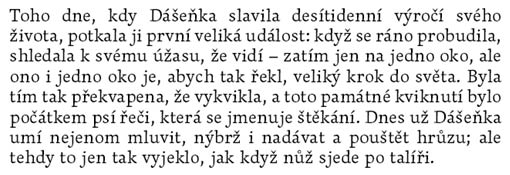
Typografie odborného textu - doplňující texty
2 Klasifikace písma Československá klasifikace písem (kterou zde uvedeme jako jedinou z mnoha možných klasifikací) je dílem typografa Jana Solpery. Tato klasifikace nerespektuje přesně chronologický vývoj, ale především dělí písma podle vzhledu a charakteristických znaků do jedenácti skupin (uvádíme deset), přičemž každá obsahuje další podskupiny: Dynamická antikva Přechodová antikva Statická antikva Lineární písmo serifové Lineární bezserifové statické písmo Lineární bezserifové dynamické písmo Lineární antikva Kaligrafická písma Volně psaná písma Písma lomená Dynamická antikva Do této skupiny řadíme renesanční antikvy vytvořené od druhé poloviny 15. století do první poloviny 18. století (a jejich moderní modifikace). Používá se především jako knižní písmo, pozdější varianty jsou univerzálně použitelné. Dynamická antikva pozdně renesanční Adobe Caslon Pro Přechodová antikva Jako přechodové antikvy označujeme písma z druhé poloviny 18. století a jejich moderní modifikace. Písma vytváří přechod mezi dynamickými písmy (inspirovanými ručně psanými znaky) a písmy konstruovanými (statická antikva). Tato písma se využívají jako knižní s širokou použitelností. Přechodová antikva Týfa Text Statická antikva Zahrnuje antikvy konce 18. a začátku 19. století a jejich moderní modifikace. Používá se jako knižní písmo zejména pro krásnou literaturu. Statická antikva didotovská Bodoni
3 Lineární písmo serifové Písma této kategorie vychází z egyptienek 19. století a jejich moderních modifikací. Tato písma slučují znaky antikvových a lineárních písem. Lineární písmo serifové, tzv. clarendon Clarendon Lineární bezserifové statické písmo Sem patří písma vycházející z grotesků 19. století a jejich moderních modifikací. Lineární bezserifové statické písmo grotesk Dyna Grotesk Lineární bezserifové dynamické písmo Navazuje na dynamické renesanční antikvy, používá se jako titulkové, ale i knižní písmo. Lineární bezserifové dynamické písmo s nakloněnou osou Gill Sans Lineární antikva Spojuje kresebné prvky antikvových a bezserifových písem, používá se jako knižní, časopisové nebo titulkové písmo. Lineární antikva s jemnými serify Copperplate Kaligrafická písma Vycházejí z kultivovaných kaligrafických skriptů, používá se jako titulkové písmo. Kaligrafické písmo dynamické Zapf Chancery
4 Volně psaná písma Vycházejí ze současných rukopisných skriptů, používají se jako titulková písma. Volně psaná lineární antikva Time Script Lomená písma Vyvíjela se od gotiky až do 19. století, používají se jako písma titulková a akcidenční. Lomené písmo fraktura Fette Fraktur
5 Klasifikace písma Písmová rodina Volbě písma bychom měli být velice obezřetní. Rozhodně bychom se neměli spokojit s písmem, jenž náš editor nabízí jako výchozí a starat se pouze o jeho velikost. Použitý font zančně ovlivní celou naši práci. Nikomu nedoporučujeme spolehnout se na font Times New Roman od Microsoftu, který v české modifikaci trpí značně nepovedenou diakritikou, navíc výsledek vypadá obvykle tuctově a kancelářsky. Přitom v samotném systému Windows nalezneme písma, která se pro sazbu hodí mnohem více. Jmenujme například font Georgia a v novějších instalacích aplikací od Microsoftu pak máme k dispozici například font Cambria. Pokud nám na výsledku záleží a chceme produkovat originálně zpracované texty, doporučujeme poohlédnout se po nějakém z nesystémových fontů. Je pravda, že většina kvalitních fontů je komerčních, ale existují písma, která můžeme používat zdarma, obsahují českou diakritiku a dobře vypadají. Uveďme zde alespoň písma Lido od Střešovické písmolijny a Gentium. Pro více fontů viz: Velikost písma Hovořit zde o velikosti písma může být značně zavádějící, neboť u každého fontu nabývá písmeno při stejné velikosti různé výšky. Pokud bychom snad přeci jen měli nějakou hodnotu doporučit, volili bychom stupeň 11. Musíme však toto variovat vzhledem ke zvolenému fontu, velikosti stránky a jejím okrajům. Doporučujeme stránku nejprve vysázet v různých stupních (například 10, 11 a 12), vytisknout, porovnat a podle výstupu finální velikost písma rozhodnout. Pokud kombinujeme více velikostí písma (pro odlišení jednotlivých úrovní nadpisů, či za jiným účelem), mělo by platit, že jednotlivé velikosti od sebe musí být jednoznačně odlišitelné volíme velikost tak, aby mezi jednotlivými použitými nebyl rozdíl velikosti méně než dva stupně. Kombinování písem Existuje pravidlo, které se hodí na většinu situací a jeho aplikací obvykle nic nezkazíme: Zvolme si jedno bezpatkové písmo jako nadpisové a jedno patkové (serifové) písmo na veškerý ostatní text. Nemusíme se tohoto pravidla striktně držet, ale mělo by platit, že rozdíly mezi jednotlivými použitými písmy by měly být výrazné, abychom čtenáři umožnili se v tatko členěném textu snadno orientovat. Použití několika velmi podobných písem by vedle sebe nevypadalo dobře a neplnilo by navigační úlohu.
6 Odstavec Hlavním a nejviditelnějším paramerem odstavce je jeho zarovnání. Pro sazbu odstavce máme čtyři možnosti: zarovnání na levý a na pravý praporek (na levou a pravou zarážku), na osu (nebo také na střed) zarovnání do bloku. Na levý praporek Tento způsob zarovnání se používá například pro sazbu veršů, často se používá pro úpravu odborných časopisů. V součastnosti jsme zvyklí vídat většinu souvislých textů zarovnaných do bloku, na sazbě na praporek však není nic špatného ani amatérského, takto zarovaný text je dobře čitelný a nehrozí nám komplikace jako u sazby do bloku (viz dále). Začátky jednotlivých řádků jsou zarovnány k levému okraji, konce řádků jsou ponechány volně, řádky jsou tedy různě dlouhé. Mezislovní mezery jsou stejné. Na pravý praporek Levý okraj řádků zůstává volný, pravý okraj je zarovnaný. Tento typ zarovnání se pro delší texty příliš nehodí, neodpovídá přirozenému čtení od levého okraje a jeho čtení je pomalejší a čtenáře více unavuje. Používá se pro sazbu poznámek na sudých stranách, nebo u popisu obrázků. Sazba na osu tato úprava odstavce se používá k sazbě veršů a k sazbě textů menšího rozsahu (nejčastěji) v akcidenčních tiskovinách (vizitky, plakáty...). Oba okraje řádku jsou volné, opět platí, že delší odstavce zarovnané na osu jsou náročnější na čtení.
7 Sazba do bloku nejpoužívanější a pro dlouhé souvislé texty nejvhodnější odstavcové zarovnání. Oba okraje řádku jsou zarovnané, všechny řádky jsou stejně dlouhé (výjimku může tvořit první a poslední řádek odstavce). Při sazbě do bloku je třeba volit vhodnou velikost písma vzhledem k šířce řádku (tedy raději menší), neboť pro dosažení shodné délky řádků upravuje sazební algoritmus mezislovní mezery a některé řádky mohou být hůře čitelné a hrozí vznik tzv. řek. Riziko vzniku řek a příliš děravých řádků můžeme snížit tím, že budeme v dokumentu dělit slova. To ovšem přináší další potenciální rizika... Nevhodně zarovnaný odstavec s ukázkou řeky